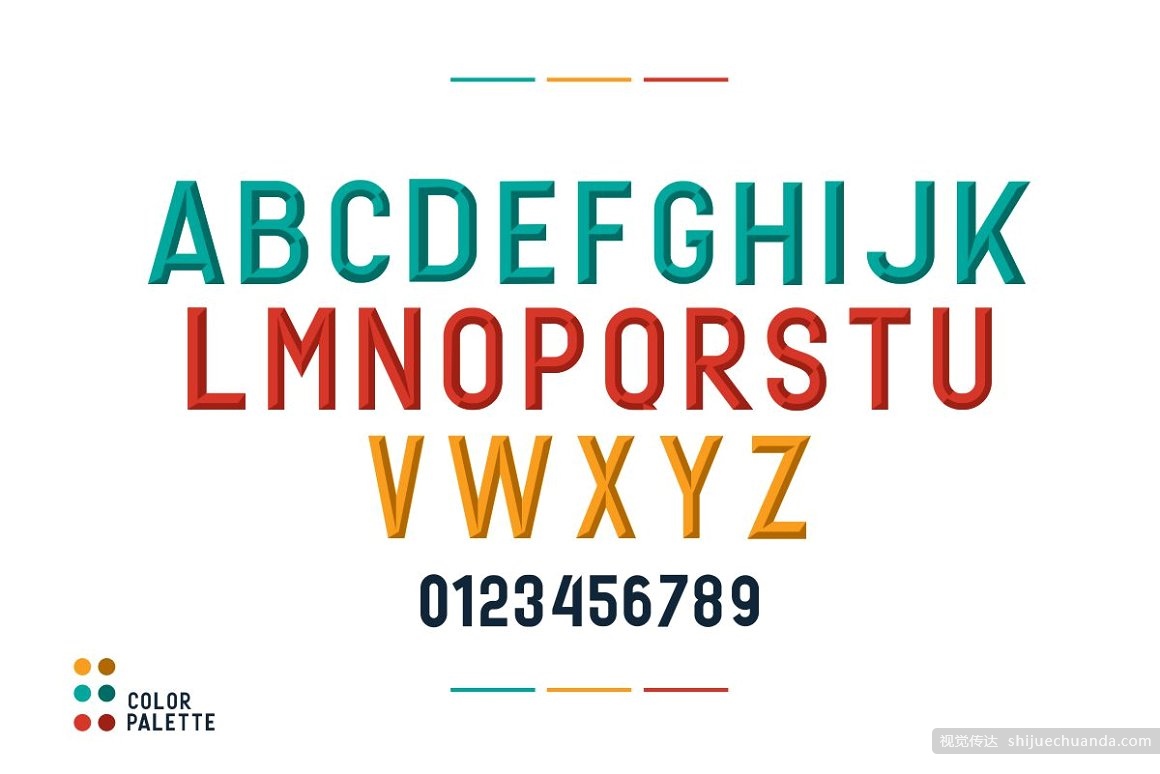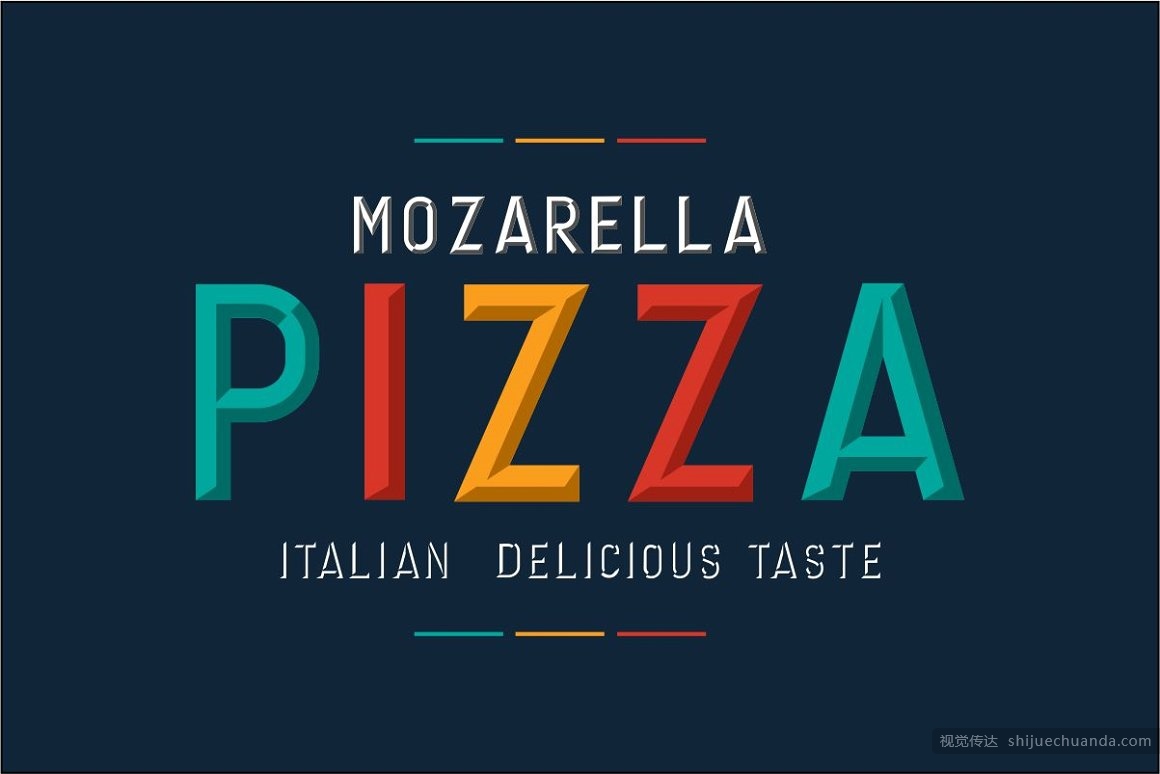
Geronimo Typeface Layer – 自带投影效果的英文标题字型下载
Geronimo是一种新型项目字体,我目前以所有分层触摸屏的形式发布,例如胶印通常用于特殊画家的标记,以使其具有吸引力和现代感,但具有良好的美学效果,此字体非常适合用于各种设计应用程序,例如商标,徽标,设计t恤,海报,UI和ux等。
您可以输入名称或输入一个单词。只需使用2层,或者在同一位置复制粘贴,即可在Adobe Photosop和Illustrator等使用的软件中非常轻松地使用它。为geronimo深色选择深色或阴影,为geronimo深色选择浅色…!提供TTF,OTF,WOFF格式下载。